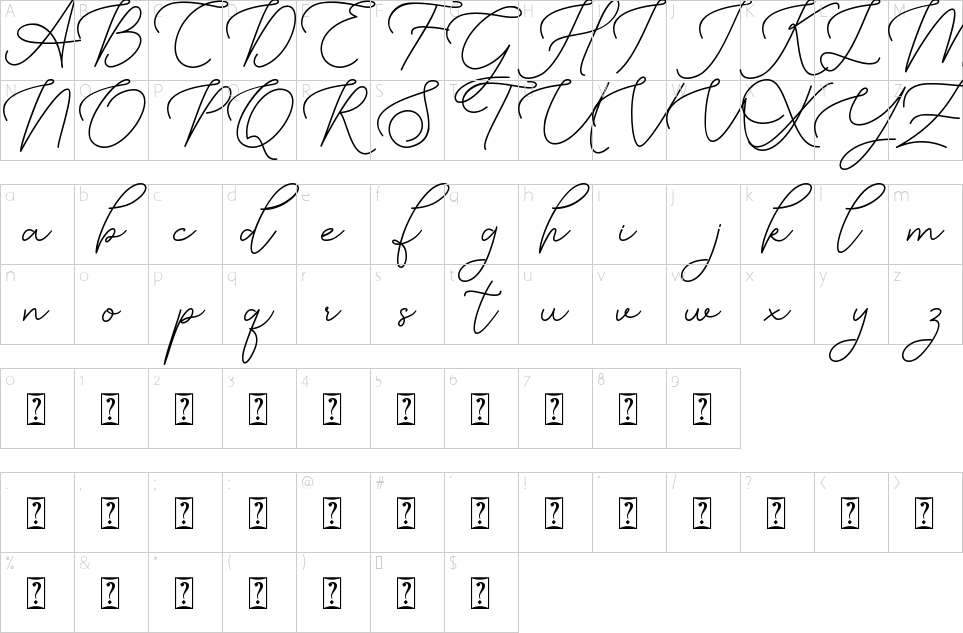
A Manhattan Signature é uma elegante e sofisticada fonte gráfica que adicionará uma dose de glamour a qualquer projeto de design. Desenvolvida pela Nox Studio, essa fonte foi projetada para dar vida a qualquer texto, tornando-o ainda mais atraente e distintivo. Com seu design arrojado, a Manhattan Signature é perfeita para criar um impacto visual imediato em seus materiais de comunicação. Ela é uma excelente escolha para designers que buscam uma fonte moderna e poderosa, que se adapta bem tanto em ambientes digitais quanto em impressão. Com um design cuidadosamente pensado, a Manhattan Signature é uma fonte de gravação que merece estar em seu arsenal de recursos. Esta fonte é disponível gratuitamente para download tanto em Windows quanto em Mac, tornando-a uma escolha perfeita para qualquer designer ou desenvolvedor de sites que está procurando por uma opção de fonte de alta qualidade.